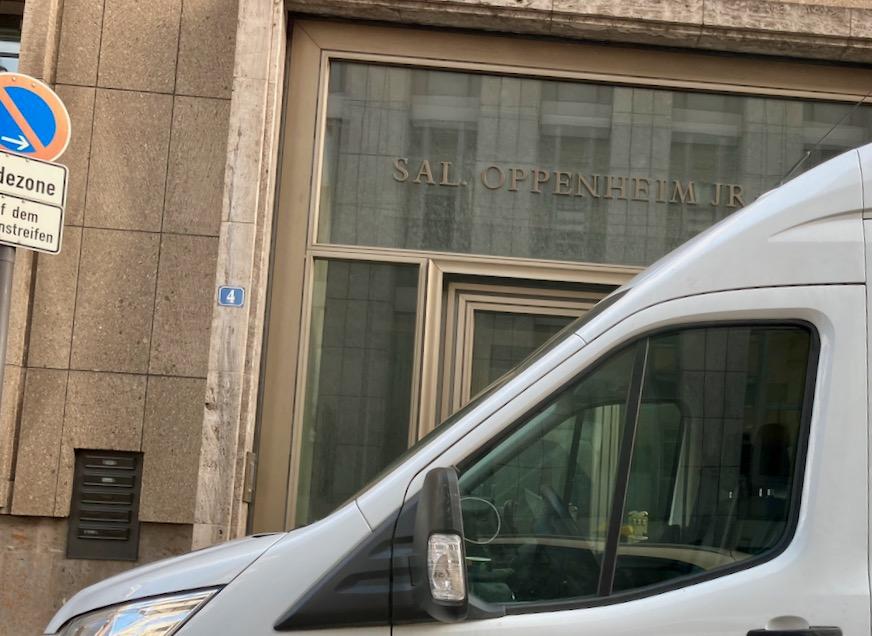
Welche Schrift Logo Sal. Oppenheim
Weiss jemand mit welcher Schrift die Versalien gesetzt sind?
Kleine Randbemerkung: Bin heute in Köln an der Bank vorbeigefahren – bei der Gebäudebeschriftung hatte das A nicht diese markante kleine Verlängerung nach links oben, die oben im Eröffnungspost zu sehen ist.
Nee, ich glaube nicht! Ich bin da aber auch nur ganz ahnungslos vorbeigefahren, hab’s aus dem Augenwinkel gesehen und dann primär aufs A geachtet. Ich meine, die Schrift war auf Mauerwerk montiert, will es aber nicht beschwören. Vielleicht bekomme ich den Schriftzug am Mittwoch bei der Rückfahrt noch mal zu sehen, dann passe ich besser auf! :-D
Mit den falsch herum montierten Buchstaben?
So, diesmal habe ich den Schriftzug für Dich eingefangen, Du hattest recht!